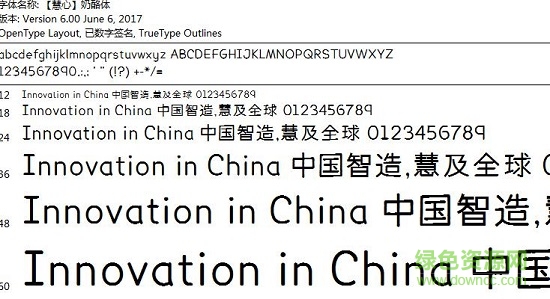
慧心的奶酪體ttf是一款整體效果明顯的電腦中文字體,這款字體根據(jù)黑體字體演變而來,加入了一些手寫字的風(fēng)格,有喜歡的朋友歡迎下載使用!
慧心奶酪體是慧心分享的一款非常有特色的黑體字體,這款字體最突出的表現(xiàn)就是整體效果醒目,并且字跡工整,筆畫清晰,適合用來進(jìn)行藝術(shù)創(chuàng)作!